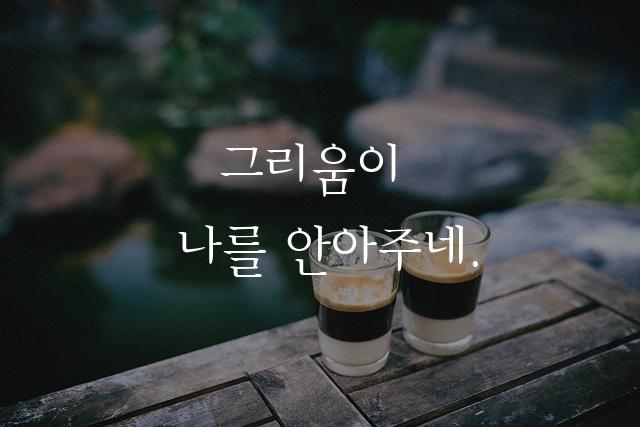
성동고딕은 성동구청에서 제작한 기본적인 고딕 스타일의 폰트입니다. 깔끔하고 명료한 선들로 독자의 이해를 도우며, 모던하면서도 실용적인 디자인을 자랑합니다.
성동고딕은(는)
기본 고딕, 감성적인, 부드러움 계열의 생김새를 가지고 있으며
웹/앱 디자인, 프레젠테이션, 보고서/문서 등에서 자주 활용되며, 효과적인 메시지 전달에 적합합니다.
이 폰트는 크리에이티브, 기술/IT, 금융/비즈니스 분야에 잘 어울리며,
명확한, 전문적인, 단순한 느낌을 담고 있는 것이 특징입니다.
이 폰트와 유사한 폰트로는 나눔고딕, 맑은고딕, 스포카 한 산스 등이 있어요. 함께 비교해 보시면 좋습니다!